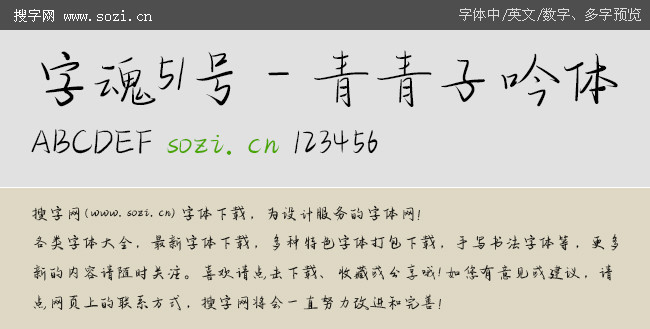
字魂51號-青青子吟體
搜字網(wǎng)提供一款字魂51號-青青子吟體中文字體下載,該字體是一款硬筆手寫字體,該字體包含6763個中文、字母、 符號和數(shù)字,具有優(yōu)雅、古典、中國風 的風格,可以滿足您設(shè)計上的各種需求,該字體主要用于導視、海報企宣、正文、書籍、報紙、美食餐飲 等場景。